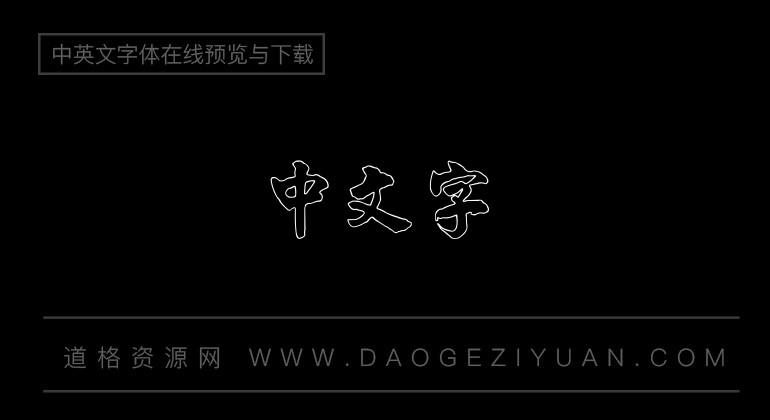
金梅碑楷字形空心字体是一种楷书字体,其特点是字体笔画粗细均匀,笔画粗细均匀,笔画流畅,笔画精细,字形精细,空心字体,空心字体让字体更加精细,更加简洁大方,更加显得轻盈,显得更加细腻,更加精致,更加清新,更加柔和。文件名:JinMeiBeiKaiZiXingKongXin-1.ttf
金梅碑楷字形空心是一款非常不错的手写艺术字体,具有很好的视觉感,适合于文化类的宣传设计、商业类品牌的广告和产品包装设计以及个性化文字排版等较多场景。